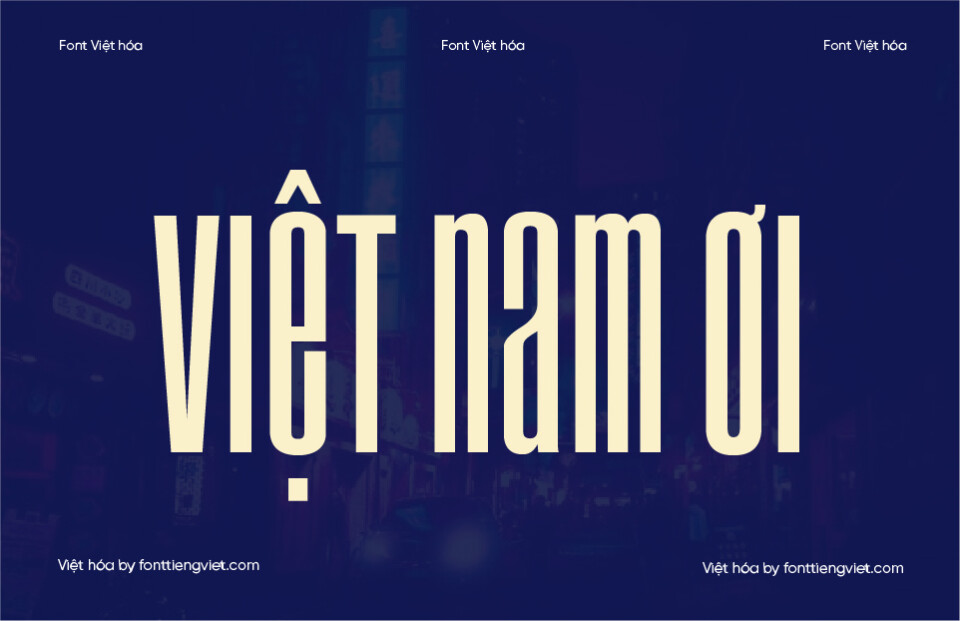
Font Việt hóa 1FTV VIP Droid 1997
Font Việt hóa 1FTV VIP Droid 1997 – Bộ Font Chữ Hoài Cổ Đẳng Cấp Cho Thiết Kế
Giới thiệu về bộ Font Việt hóa 1FTV VIP Droid 1997 trong thiết kế đồ họa
Trong thế giới sáng tạo nội dung hiện nay, việc lựa chọn một bộ Font Miễn Phí chất lượng đóng vai trò then chốt giúp truyền tải thông điệp hiệu quả. Đặc biệt, bộ Font Việt hóa 1FTV VIP Droid 1997 đã nhanh chóng trở thành tâm điểm chú ý nhờ sự kết hợp hoàn hảo giữa nét cổ điển và tính ứng dụng hiện đại. Được lấy cảm hứng từ những năm cuối thế kỷ 20, bộ font này mang đến một luồng gió mới, giúp các bạn học sinh và giáo viên dễ dàng tạo ra những bài thuyết trình ấn tượng hay các ấn phẩm học đường sinh động. Với việc được tối ưu hóa tiếng Việt hoàn chỉnh, người dùng sẽ không còn gặp phải lỗi hiển thị ký tự hay mất dấu, đảm bảo tính thẩm mỹ cao nhất cho mọi văn bản.
Tại sao Font Việt hóa 1FTV VIP Droid 1997 lại được ưa chuộng?
Lý do hàng đầu khiến Font Việt hóa 1FTV VIP Droid 1997 trở nên phổ biến chính là sự tinh tế trong từng đường nét. Các ký tự được thiết kế với độ dày vừa phải, tạo cảm giác chắc chắn nhưng không kém phần thanh thoát. Đây là lựa chọn lý tưởng cho những ai muốn theo đuổi phong cách Retro hoặc Vintage đang rất thịnh hành. Ngoài ra, tính tương thích của bộ font này trên các phần mềm thiết kế phổ biến như Photoshop, Canva hay Microsoft Word là một điểm cộng lớn. Đối với môi trường giáo dục, bộ font này giúp các tài liệu giảng dạy trở nên thân thiện và dễ tiếp cận hơn đối với người học, tạo sự hứng thú ngay từ cái nhìn đầu tiên.
Cách ứng dụng Font Việt hóa 1FTV VIP Droid 1997 hiệu quả nhất
Để tận dụng tối đa vẻ đẹp của Font Việt hóa 1FTV VIP Droid 1997, người dùng cần lưu ý đến cách phối hợp màu sắc và bố cục. Bộ font này hoạt động tốt nhất trên các phông nền có màu trầm hoặc tông màu pastel nhẹ nhàng. Việc sử dụng font làm tiêu đề cho các báo cáo, bìa sách hoặc poster sự kiện sẽ tạo ra điểm nhấn thị giác mạnh mẽ. Trong các bài giảng điện tử, thầy cô có thể dùng font này để làm nổi bật các từ khóa chính, giúp học sinh dễ dàng ghi nhớ nội dung bài học. Sự linh hoạt của nó cho phép ứng dụng từ các biểu mẫu trang trọng đến các thiết kế sáng tạo tự do mà vẫn giữ được hồn cốt của bản thiết kế gốc.
Lưu ý khi sử dụng các bộ font việt hóa hiện nay
Kết luận về giá trị của Font Việt hóa 1FTV VIP Droid 1997
Tổng kết lại, bộ Font Việt hóa 1FTV VIP Droid 1997 không chỉ đơn thuần là những ký tự vô hồn mà là công cụ đắc lực hỗ trợ tư duy sáng tạo. Với sự tỉ mỉ trong quá trình việt hóa, bộ font này đã đáp ứng đầy đủ nhu cầu của người dùng tại Việt Nam, từ lĩnh vực giáo dục đến truyền thông. Việc sở hữu một kho tàng Font Miễn Phí, Font Việt Hóa, Font Việt hóa 1FTV VIP Droid 1997 đa dạng sẽ giúp bạn tự tin hơn trong mọi dự án thiết kế cá nhân. Hãy bắt đầu trải nghiệm và làm mới những trang văn bản của mình bằng sự độc đáo mà bộ font này mang lại ngay hôm nay để thấy được sự khác biệt vượt trội trong từng sản phẩm sáng tạo.